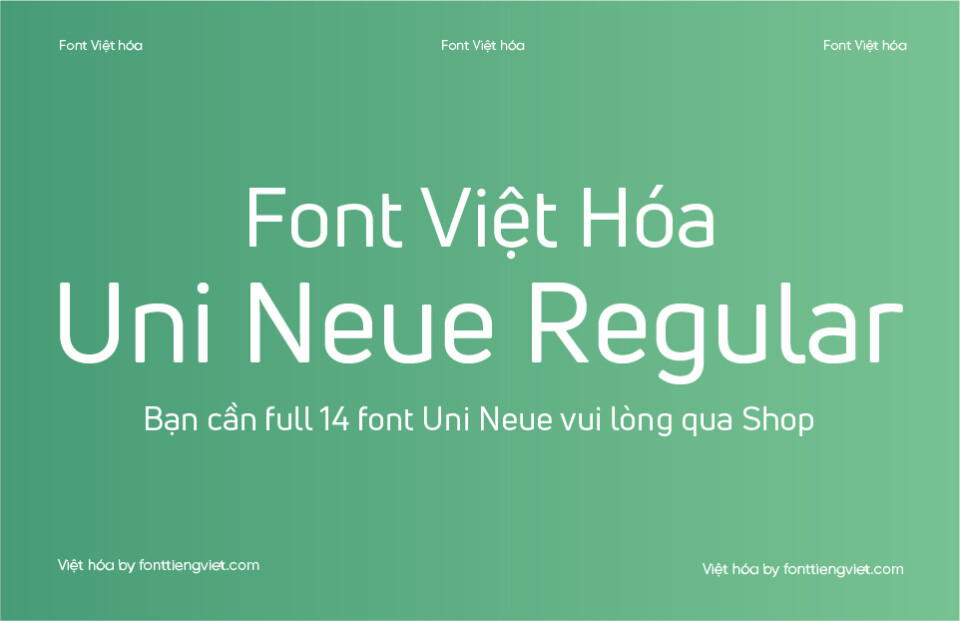
Font Việt hóa 1FTV Uni Neue Regular – Cần full 14 font qua shop nhé: Sự lựa chọn hoàn hảo cho thiết kế hiện đại
Giới thiệu về Font Việt hóa 1FTV Uni Neue Regular – Cần full 14 font qua shop nhé
Trong thế giới thiết kế đồ họa, việc lựa chọn một Font Miễn Phí chất lượng luôn là ưu tiên hàng đầu của các nhà sáng tạo. Đặc biệt, bộ Font Việt hóa 1FTV Uni Neue Regular – Cần full 14 font qua shop nhé đã nhanh chóng trở thành tâm điểm chú ý nhờ sự kết hợp hài hòa giữa phong cách hiện đại và khả năng hiển thị tiếng Việt hoàn hảo. Uni Neue vốn là một nhánh phát triển từ họ phông chữ Uni Sans nổi tiếng, mang trong mình những đường nét bo góc tinh tế, tạo cảm giác thân thiện nhưng vẫn giữ được vẻ ngoài chuyên nghiệp. Phiên bản Regular này được tối ưu hóa đặc biệt để phục vụ cho các mục đích soạn thảo văn bản, thiết kế giao diện web hoặc trình bày slide bài giảng một cách rõ nét nhất.
Tại sao bạn nên chọn Font Việt hóa 1FTV Uni Neue Regular?
Một trong những lý do khiến Font Việt hóa 1FTV Uni Neue Regular – Cần full 14 font qua shop nhé được yêu thích chính là sự tỉ mỉ trong khâu Việt hóa. Các dấu câu tiếng Việt được đặt ở vị trí chuẩn xác, không bị lỗi hiển thị khi gõ trên các phần mềm thiết kế như Photoshop hay Illustrator. Điều này giúp tiết kiệm thời gian đáng kể cho người dùng, đặc biệt là các bạn học sinh, sinh viên khi làm báo cáo. Bên cạnh đó, độ dày của nét chữ Regular rất vừa phải, tạo nên sự cân bằng thị giác tuyệt vời, giúp người đọc không bị mỏi mắt khi tiếp cận những nội dung dài.
Đặc điểm nổi bật của bộ font Uni Neue chuyên nghiệp
Khi nhắc đến dòng Uni Neue, chúng ta không thể bỏ qua tính đa dụng của nó. Mặc dù phiên bản Regular là phổ biến nhất, nhưng để tạo ra một tác phẩm thiết kế có chiều sâu và phân cấp thông tin rõ ràng, người dùng thường cần sự kết hợp của cả gia đình chữ. Đó là lý do tại sao cụm từ Font Việt hóa 1FTV Uni Neue Regular – Cần full 14 font qua shop nhé thường đi kèm với lời nhắn nhủ về bộ sưu tập đầy đủ. Việc sở hữu trọn bộ 14 kiểu từ mỏng đến đậm sẽ giúp bạn linh hoạt hơn trong việc nhấn mạnh các tiêu đề chính hoặc chú thích nhỏ.
Ứng dụng thực tế trong giáo dục và đời sống
Trong môi trường học đường, Font Việt hóa 1FTV Uni Neue Regular – Cần full 14 font qua shop nhé đóng vai trò quan trọng trong việc xây dựng các tài liệu giảng dạy trực quan. Giáo viên có thể sử dụng font chữ này để làm nổi bật các ý chính trên bảng đen điện tử hoặc trong các tập san trường học. Với phong cách geometric pha chút nhân văn, bộ font này mang lại cảm giác hiện đại, kích thích sự sáng tạo của học sinh. Ngoài ra, trong các dự án khởi nghiệp nhỏ, đây cũng là công cụ đắc lực để thiết kế logo và bộ nhận diện thương hiệu tối giản nhưng vô cùng sang trọng.
Hướng dẫn sử dụng và trải nghiệm trọn bộ font chữ
Để đạt được hiệu quả thẩm mỹ cao nhất, người dùng nên kết hợp Uni Neue Regular với các font chữ có chân (serif) khác để tạo sự tương phản. Tuy nhiên, nếu bạn muốn một phong cách đồng nhất và hiện đại hoàn toàn, việc sử dụng toàn bộ hệ sinh thái Uni Neue là giải pháp tối ưu. Hãy lưu ý rằng, phiên bản miễn phí thường chỉ cung cấp bản Regular để trải nghiệm cơ bản. Nếu dự án của bạn yêu cầu sự cầu kỳ và đầy đủ các sắc thái biểu cảm, đừng ngần ngại tìm kiếm bản full để có trải nghiệm tốt nhất.
Kết luận về giải pháp thiết kế với Uni Neue
Tóm lại, Font Việt hóa 1FTV Uni Neue Regular – Cần full 14 font qua shop nhé không chỉ là một phông chữ, mà là một giải pháp thiết kế toàn diện cho người dùng Việt. Sự tinh tế trong từng nét chữ và tính ứng dụng cao đã khẳng định giá trị của nó trong cộng đồng thiết kế. Nếu bạn đang tìm kiếm sự khác biệt cho tác phẩm của mình, hãy bắt đầu ngay với Font Miễn Phí, Font Việt Hóa, Font Việt hóa 1FTV Uni Neue Regular – Cần full 14 font qua shop nhé để cảm nhận sự thay đổi chuyên nghiệp nhất trong từng trang giấy.